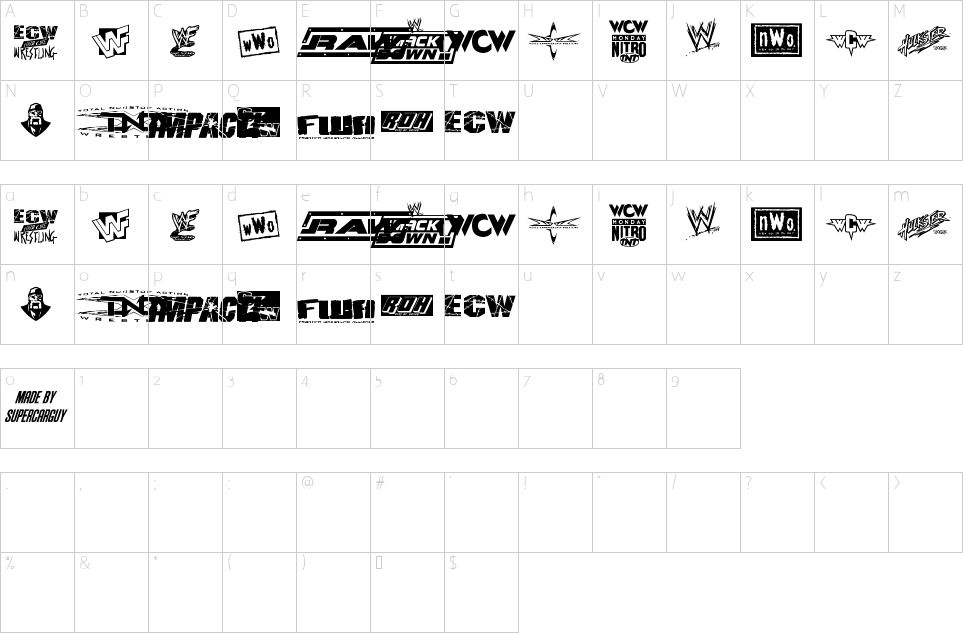
A fonte Pro Wrestling Logos é uma criação minimalista e moderna, ideal para designers que buscam elementos únicos para suas criações de logotipos de wrestling profissional. Especialmente para aqueles criando projetos para sites, aplicativos, designs de logotipos e outros ambientes digitais, esta fonte traz uma dinâmica vibrante e personalizada aos seus projetos. Ideal para quem busca uma fonte única e divertida, a Pro Wrestling Logos combina elegância e humor, ideal para expressar o espírito do wrestling profissional em suas criações. Desenvolvida pelo designer Steve Ferrera, esta fonte foi feita para atender a um público diversificado, desde os amantes de wrestling até aqueles que buscam uma fonte versátil para diferentes usos. Com mais de 27 mil downloads, a Pro Wrestling Logos se tornou um recurso popular entre os designers gráficos, oferecendo um design único que adiciona um toque especial aos seus projetos.